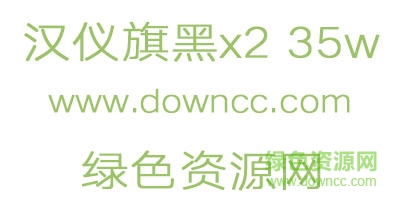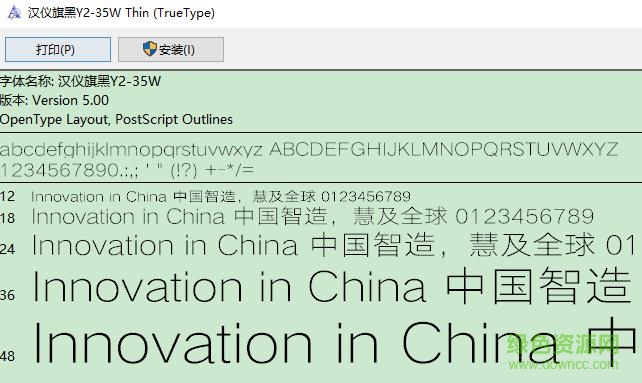
漢儀旗黑X2-35W字體
漢儀旗黑X2 35W是漢儀官方打造的一款簡體中文字體,這款漢儀字體結(jié)構(gòu)設(shè)計簡約,筆畫纖細(xì),整體效果非常出色,有興趣的朋友就來綠色資源網(wǎng)下載吧!
漢儀旗黑x2-35W字體信息
字體全稱:漢儀旗黑x2-35W ExtraLight
來源類型:官方發(fā)行
字體家族:漢儀旗黑x2-35W
字體風(fēng)格:Extra Light
字體公司:漢儀字庫
字體設(shè)計師:張暄
漢儀旗黑字體介紹
漢儀旗黑是由三個系列字體(長、方、扁)組成的一個龐大而完整的家族字體,從最細(xì)的25到最粗的105,共計15個字重,是迄今為止國內(nèi)最大、最豐富的字重的家族字體,可以滿足企業(yè)多渠道,全方位的內(nèi)容設(shè)計以及定制化需求,實現(xiàn)企業(yè)品牌形象在各渠道的統(tǒng)一呈現(xiàn)